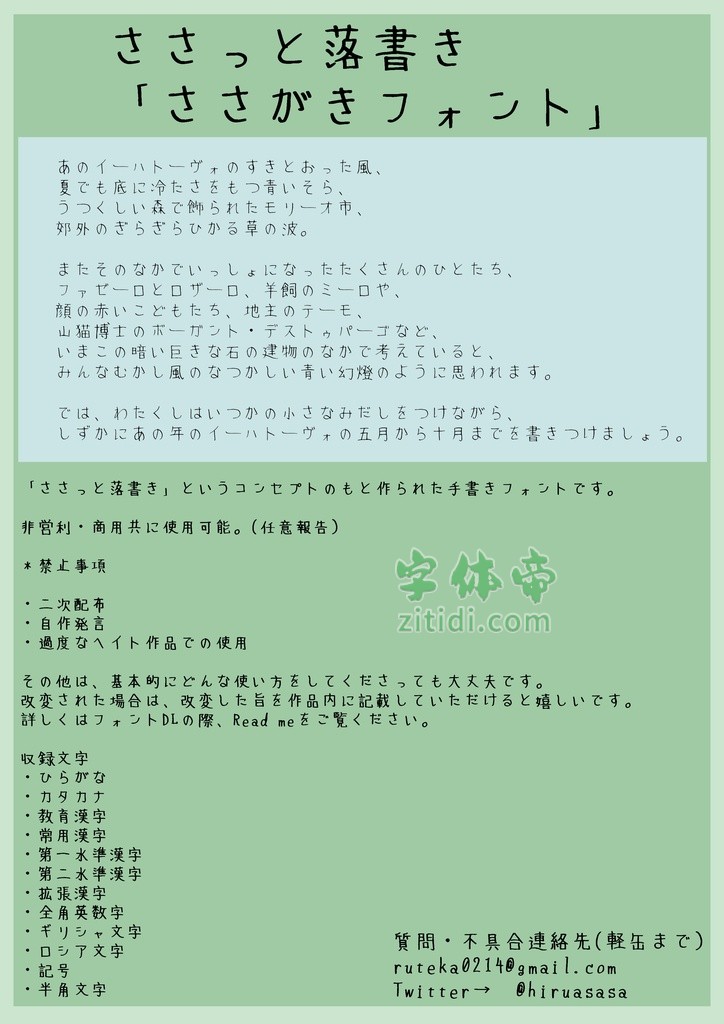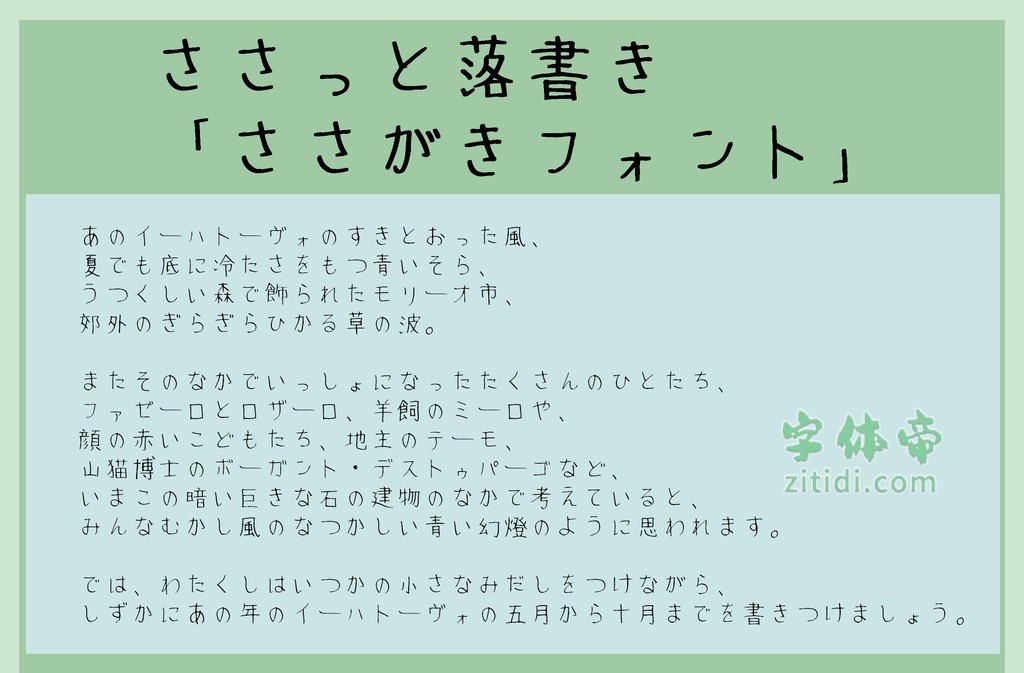
佐佐木字体字体信息
一种手写的免费字体,可以按原样删除作者的手写字符。
[记录字符]
- 平假名
- 片假名
- 教育汉字
- 常用汉字
- 第一水准汉字
- 第二水准汉字
- 扩张汉字
- 全角英数字
- 希腊字母
- 俄文字母
- 记号
- 半角文字
“佐佐木字体”是一款书写很新颖的字体,字体大方,适合各种设计作品使用!欢迎下载!